1. Mahfuj Bangla Font Review
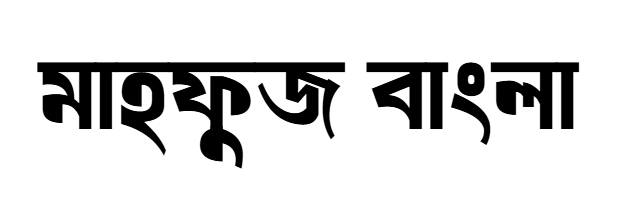
Mahfuj Bangla Font একটি ক্লাসিক টাইপফেস, যেটা traditional ও modern এর মাঝামাঝি একটা balanced look দেয়। এই ফন্টের অক্ষর গঠন পরিষ্কার, stroke খুব বেশি decorative না, আবার একেবারে সাদামাটা ও না। ফলে এটি headline এবং subheading দুই জায়গাতেই ব্যবহারযোগ্য।
Photoshop ও Illustrator ব্যবহারকারীদের জন্য এই ফন্টের সবচেয়ে বড় সুবিধা হলো এটি সাধারণত TTF ফরম্যাটে পাওয়া যায় এবং install করার পর সরাসরি সফটওয়্যারে show করে। Unicode support থাকায় বিজয় ঝামেলা ছাড়াই typing করা যায়। যারা YouTube thumbnail, Facebook cover, banner বা promotional poster ডিজাইন করেন, তাদের জন্য এটি safe choice।
Design perspective থেকে দেখলে, এই ফন্ট bold weight এ বেশি ভালো দেখায়। Light বা regular size-এ body text হিসেবে ব্যবহার করলে impact কিছুটা কমে যায়। তাই এটি paragraph এর জন্য না, বরং short impactful text এর জন্য বেশি উপযুক্ত।
যেখানে ব্যবহার করবেন:
• Event poster headline
• YouTube thumbnail text
• Branding tagline
• Social media graphic
যেখানে ব্যবহার না করাই ভালো:
• দীর্ঘ article body
• বইয়ের paragraph
Overall, আপনি যদি clean কিন্তু authoritative Bangla font for Photoshop খুঁজে থাকেন, Mahfuj একটি dependable option।
2. Madinawala Normal Version Review
Madinawala Normal Version নাম থেকেই বোঝা যায় এটি একটি simple ও clean Bangla font। অতিরিক্ত decorative stroke নেই, overly stylish না। কিন্তু এই simplicity-ই এর শক্তি।
যারা daily graphic design করেন এবং client কাজ করেন, তারা জানেন অনেক সময় flashy font কাজ করে না। Client চায় readable, straightforward text। Madinawala ঠিক সেই কাজের জন্য।
Photoshop এ body text হিসেবে ব্যবহার করলে readable থাকে। ছোট size-এও clarity ঠিক থাকে। এটি banner, leaflet, flyer, notice design-এ ভালো কাজ করে।
তবে যদি আপনি eye-catching YouTube thumbnail বা bold branding design করেন, তাহলে এটি একটু কম dramatic মনে হতে পারে। এটি practical font, show-off font না।
Best use:
• Notice design
• Informational poster
• Newspaper style layout
• Educational material
Avoid:
• Thumbnail headline
• Creative artistic typography
আপনি যদি Bangla font for Illustrator খুঁজে থাকেন যেটা clean print-ready output দেয়, Madinawala একটি safe and practical choice।
3. Aboron Font Review
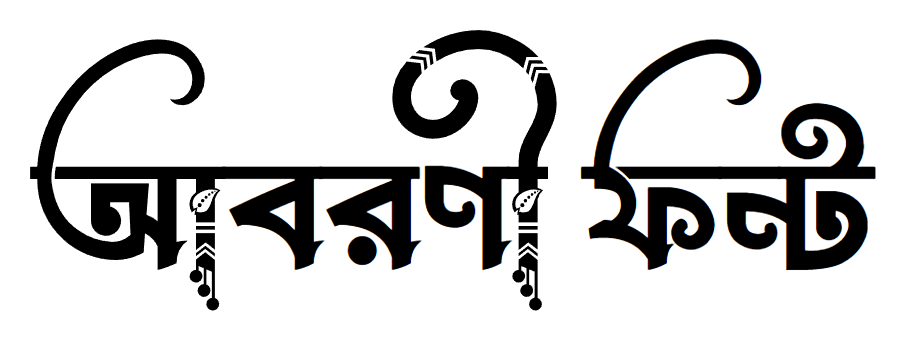
Aboron Font সাধারণত decorative vibe দেয়। এর অক্ষরের shape গুলো একটু artistic feel বহন করে। এটি headline বা single word typography-তে ভালো impact দেয়।
Photoshop-এ drop shadow, stroke বা texture যোগ করলে এটি আরো attractive হয়ে ওঠে। Illustrator-এ outline convert করলে shape manipulation সহজ হয়।
তবে এই ফন্ট body text-এর জন্য না। Paragraph এ ব্যবহার করলে readability কমে যায়। এটি impact font, reading font না।
Best use:
• Poster main title
• Festival banner
• Social media announcement
• Creative branding
Avoid:
• Long paragraph
• Small mobile text
Design sense থেকে বলতে গেলে, এটি attention grabbing font। আপনি যদি dramatic visual চান, Aboron consider করতে পারেন।
4. Elias Pospoborno Review
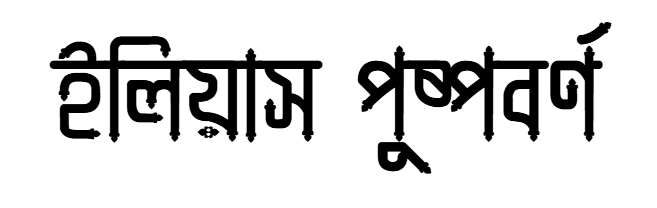
Elias Pospoborno ফন্ট সাধারণত stylistic heading-এর জন্য ভালো। এটি modern Bangla typography feel দেয়। YouTube thumbnail বা Facebook promo banner এ bold করলে ভালো attention আনে।
Photoshop-এ large size-এ ব্যবহার করলে এর character বেশি ফুটে ওঠে। তবে small text-এ sharpness কিছুটা কমে যেতে পারে।
Best use:
• Thumbnail
• Facebook ad banner
• Event headline
Avoid:
• Body content
• Long informational text
5. Mahfuj Cirkot Font Review
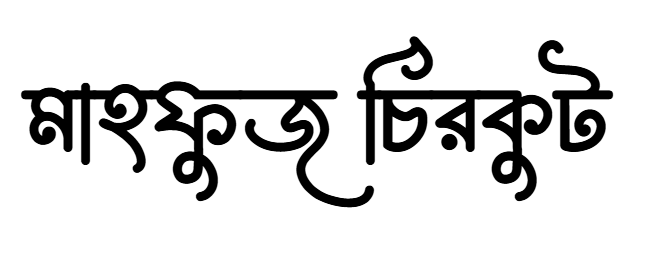
Mahfuj Cirkot একটি character-based display font। এটি creative, slightly edgy vibe দেয়। যদি আপনার design energetic, youth-focused বা bold message হয়, এটি মানাবে।
Photoshop-এ stroke + gradient দিলে খুব সুন্দর কাজ করে। Illustrator-এ vector conversion clean থাকে।
Body text-এর জন্য না। এটি headline font।
Best use:
• Campaign poster
• Youth event banner
• Strong call-to-action design
Avoid:
• Formal document
• Educational material